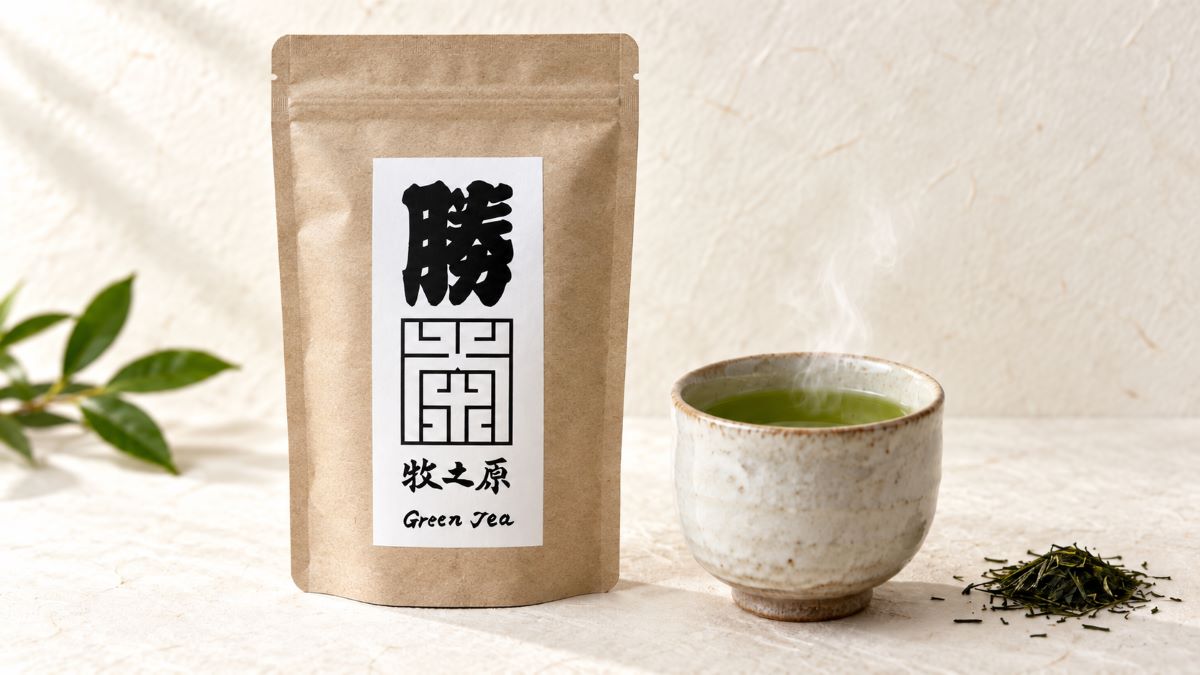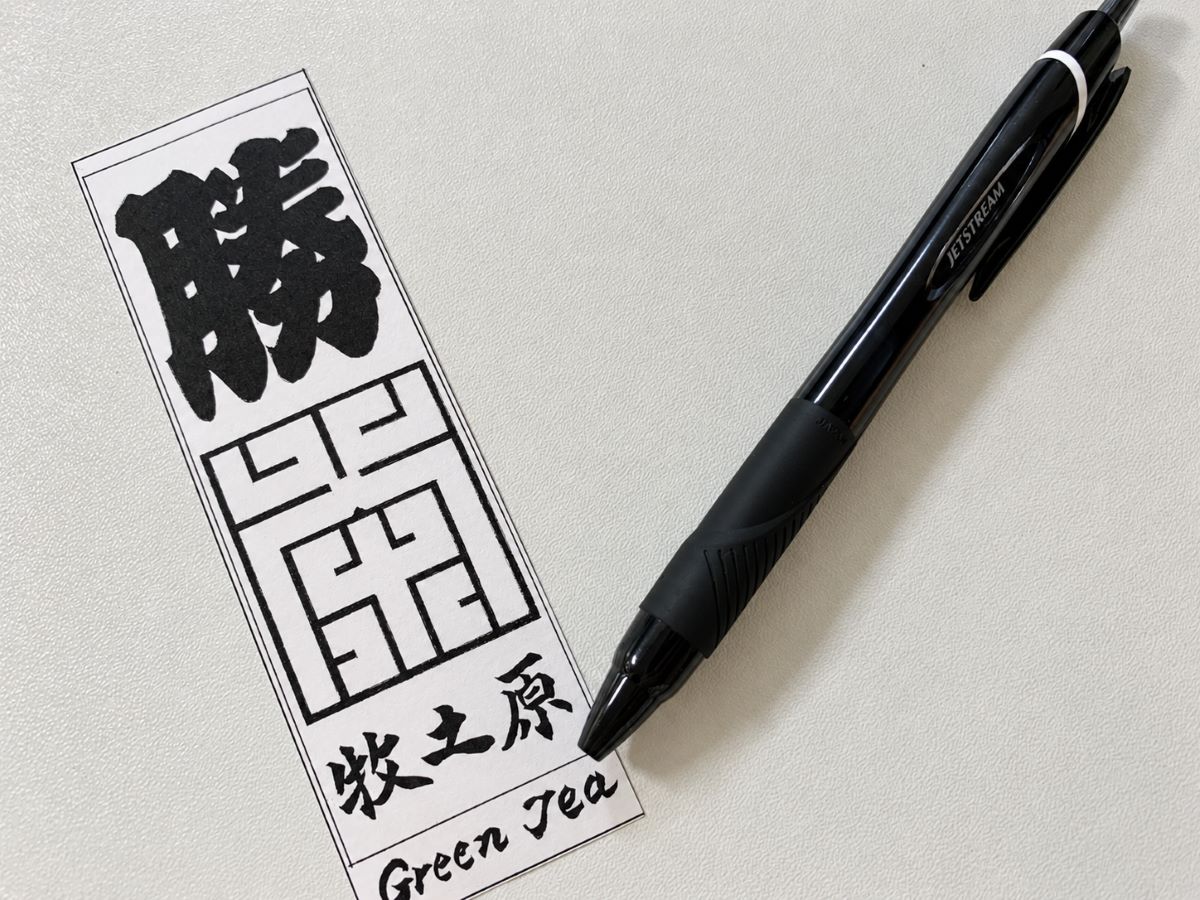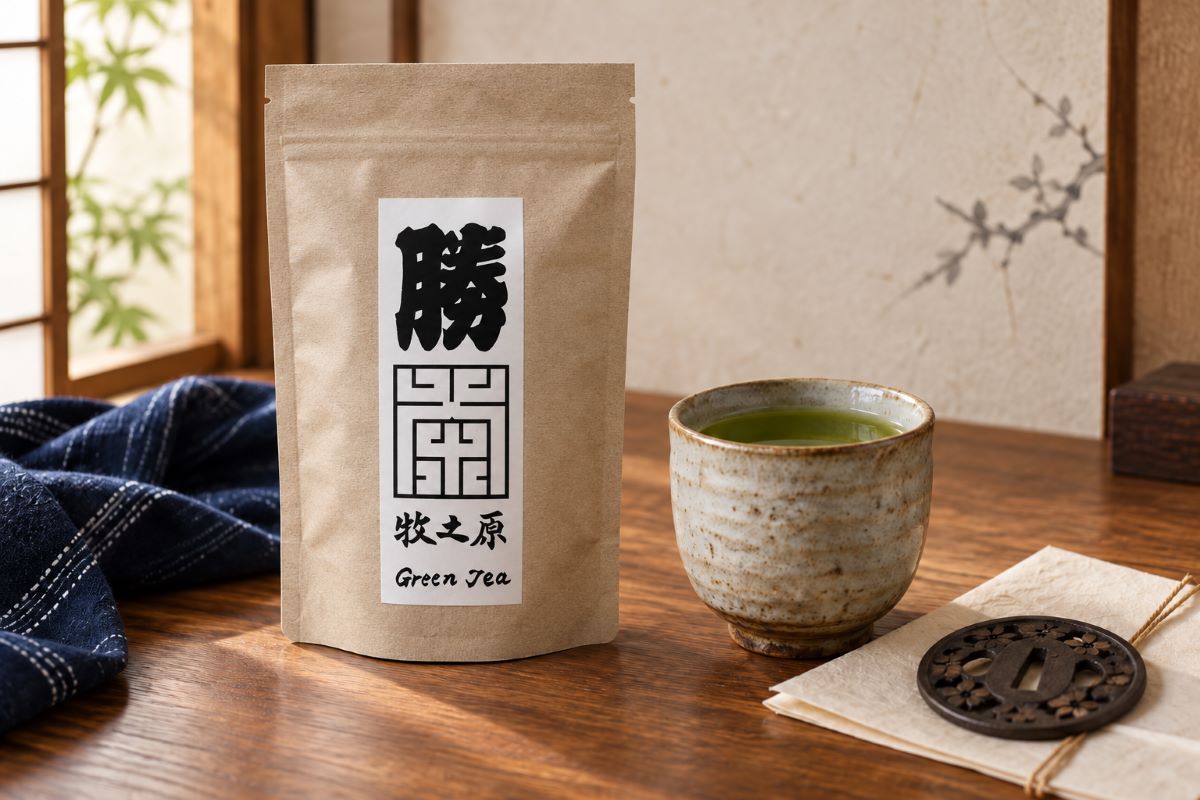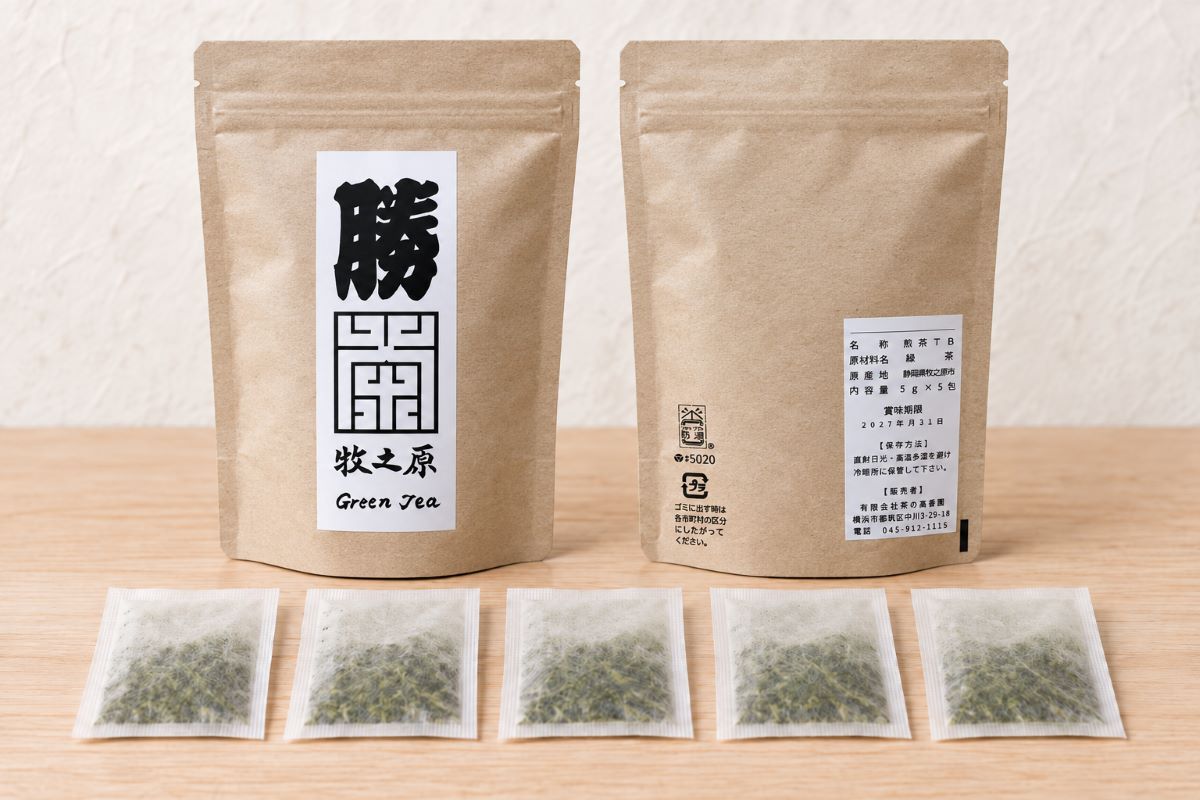
幕末の歴史が息づく築地と、旧幕臣たちが切り拓いた静岡県牧之原。
「勝茶(Katsu-cha)」は、この二つの土地を結ぶ歴史と、縁起の良い江戸文字の「勝」を一つにした、特別な日本茶です。🍵
国内の幕末・勝海舟ファンの方には、歴史に思いを馳せながら味わうお茶として。
海外の方には、困難に立ち向かった侍たちの精神を伝える、SAMURAI TEA FROM JAPANとしてお楽しみいただけます。
築地から牧之原へ
勝海舟と幕臣たちが紡いだ、再出発の物語
幕末、日本が近代国家へと歩み始めた時代。
築地には、幕府の海軍教育を担った「軍艦操練所」が置かれ、勝海舟をはじめ、日本の未来を考えた人々が海軍の近代化に関わりました。
その後、江戸幕府が終わりを迎えると、多くの旧幕臣たちは、それまでの立場や仕事を失いました。
彼らが刀を農具に持ち替え、新しい人生を切り拓くために向かった土地の一つが、現在の静岡県牧之原台地です。
厳しい自然環境の中、旧幕臣たちは茶畑を開墾し、牧之原を日本有数の茶産地へと育てていきました。
刀から鍬へ。
武士から茶の開拓者へ。
「勝茶」は、困難の中でも希望を失わず、新しい時代に挑戦した人々の物語を、一杯のお茶に込めた商品です。
江戸文字の「勝」で、運を引き寄せる
パッケージに大きく描かれているのは、力強い江戸文字の「勝」です。
この文字は、築地の江戸文字職人・有限会社 津多屋商店 加藤木大介氏が、一文字ずつ思いを込めて書き上げました。🖌️
江戸文字は、文字を太く、紙の余白をできるだけ少なく書くのが特徴です。
そこには、
「客席が隙間なく埋まる」
「お客様がたくさん訪れる」
「福が隙間なく入り込む」
という、商売繁盛や千客万来への願いが込められています。
その縁起の良い江戸文字で書かれた「勝」と、苦難を乗り越えた幕臣たちの歴史を組み合わせた勝茶は、ここ一番の勝負を応援するお茶です。
こんなときにおすすめです
- 受験や資格試験の合格祈願に
- スポーツの試合や大会の前に
- 大切な商談やプレゼンの前に
- 選挙やコンテストへの挑戦に
- 新しい仕事や事業を始める方へ
- 幕末・勝海舟・新選組など、歴史が好きな方へ
- 外国の方への日本らしいお土産に
- 頑張る家族や友人への応援ギフトに
「絶対に勝ちたい」と願う日の前に。
温かい勝茶を飲みながら心を整え、前へ進む勇気を蓄えてください。
静岡県牧之原産の本格煎茶
勝茶には、旧幕臣たちによる茶園開拓の歴史を持つ、静岡県牧之原市産の茶葉を使用しています。
製造を担当するのは、有限会社 茶の高香園です。
✓ 味わいと香り
美しい緑色と、煎茶ならではの爽やかな香り。
口に含むと、まろやかなコクと心安らぐ味わいが広がります。
和菓子との相性も良く、羊羹、お饅頭、最中などと一緒にお召し上がりいただくのもおすすめです。
✓ 手軽なティーバッグタイプ
大切な勝負の前には、ゆっくりと一呼吸。
勝茶を味わいながら、気持ちを整えてください。
幕末ファンへの贈り物に
勝海舟や幕臣たちが生きた幕末は、日本の社会が大きく変化した時代です。
勝茶は、単なるお茶ではありません。
築地の軍艦操練所、江戸城無血開城、旧幕臣たちによる牧之原の開拓という、幕末から明治へ続く歴史を味わうお茶です。
歴史好きの方への贈り物や、幕末ゆかりの地を巡る旅の記念品としてもおすすめです。
お茶を飲みながら、激動の時代を生き抜いた人々に思いを馳せてみませんか。
お茶を飲むことが、文化を未来へつなぐ
私たちNPO法人つきじ江戸文字と歴史伝承の会は、商売繁盛を願う江戸文字と、その文字とともに歴史を刻んできた築地の魅力を、次世代へ伝える活動を行っています。
江戸文字体験会や歴史を学ぶ機会を通して、手書き文字の素晴らしさと、築地の奥深い歴史を国内外の皆様へ紹介しています。
勝茶の売上は、地域の子どもたちを対象とした無料江戸文字教室をはじめ、江戸文字と築地の歴史を未来へ残すための文化継承活動に、大切に活用させていただきます。
勝茶を選ぶことは、日本の伝統文化を応援すること。
皆様の一杯が、江戸から受け継がれてきた文化を、次の世代へつなぐ力になります。
勝ちたい日に、勝茶を。
受験、試合、仕事、新しい挑戦。
人生には、勇気を出して前へ進まなければならない瞬間があります。
そんな日のために、幕末を生き抜いた人々の不屈の精神と、江戸文字の縁起を込めた勝茶をお届けします。
自分自身への一杯に。
頑張る人への応援に。
日本文化を愛する海外の方への贈り物に。
🍵 勝茶を飲んで、次の「勝」へ。